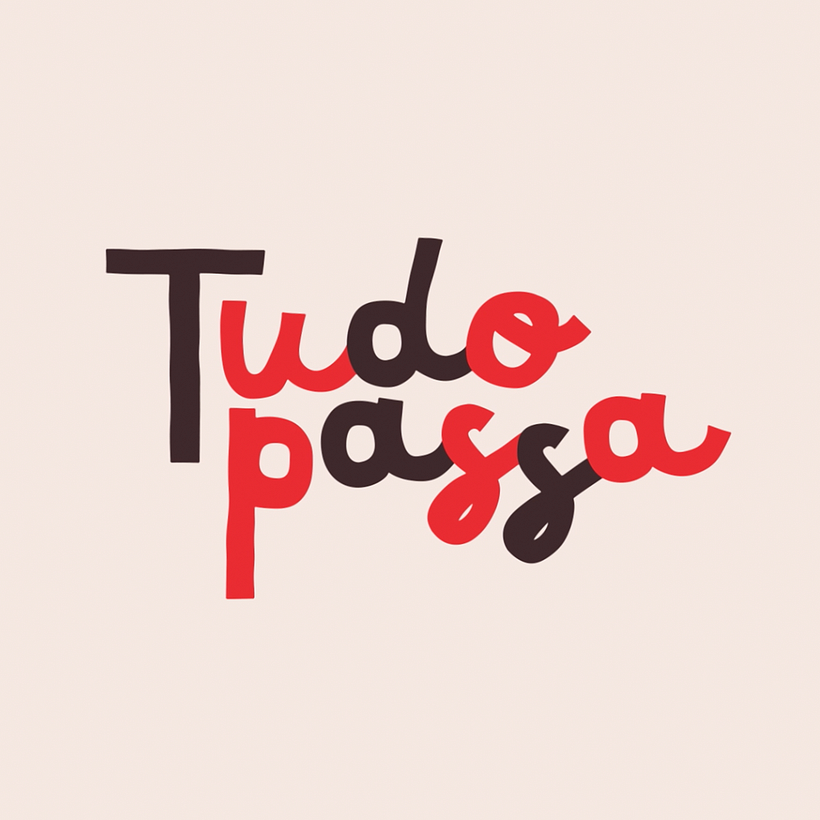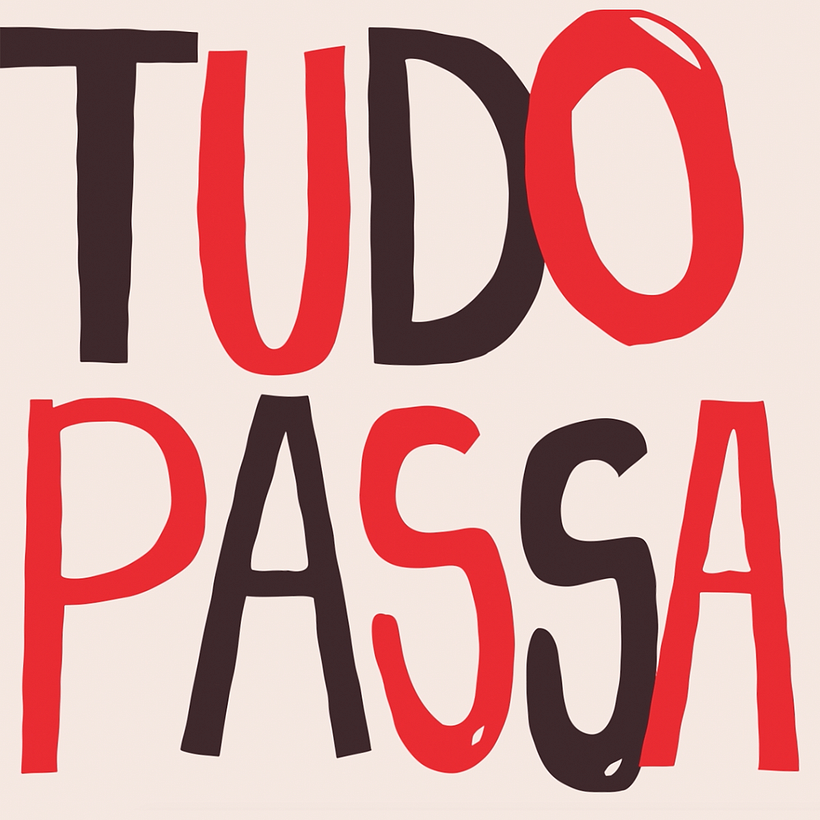
Insegnante PlusCarino! Vedo che hai riscontrato le difficoltà quando hai spostato un serif in un sans serif o hai disegnato un font! Ottimo lavoro, basta guardare quei punti vaganti quando si spostano i pesi!